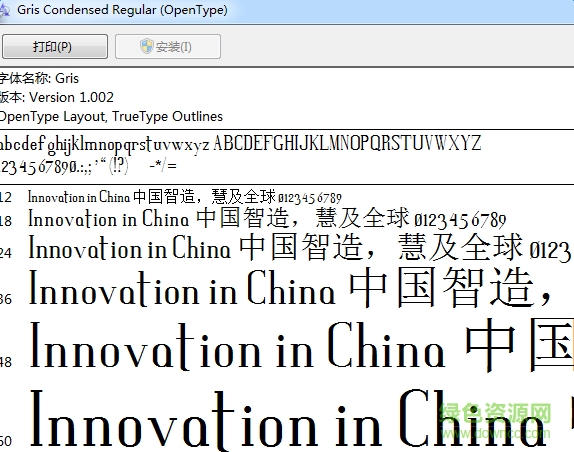
Gris英文字體
Gris字體是一款超好用的個(gè)性英文字體,該字體可以廣泛應(yīng)用于廣告設(shè)計(jì)、宣傳海報(bào)、ppt、影視制作以及任何使用文字的領(lǐng)域,有需要的朋友可以免費(fèi)下載收藏。
Gris字體是一款極具個(gè)性的字體,該字體十分飄逸,彰顯了自己的個(gè)性,有喜歡的朋友可以來綠色資源網(wǎng)下載使用!